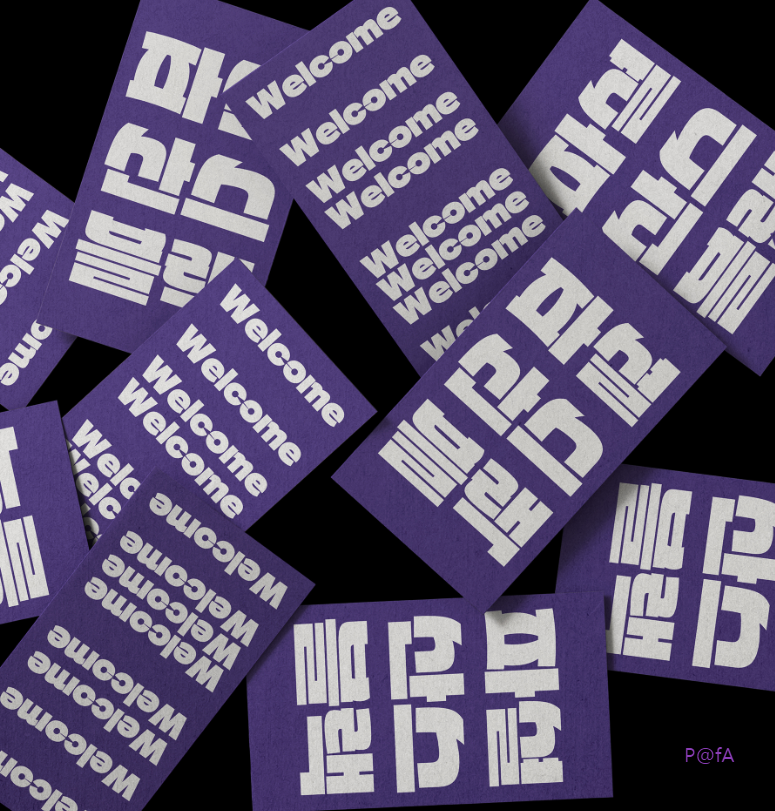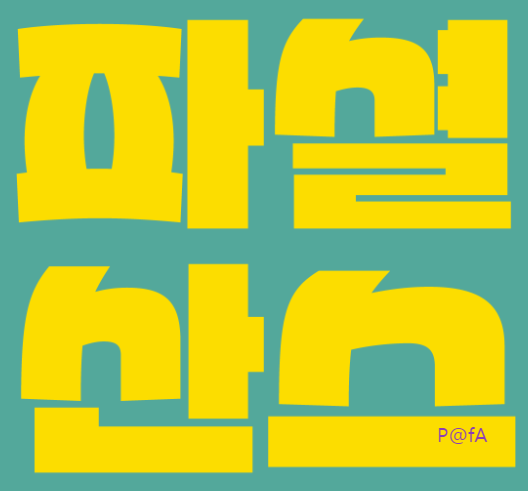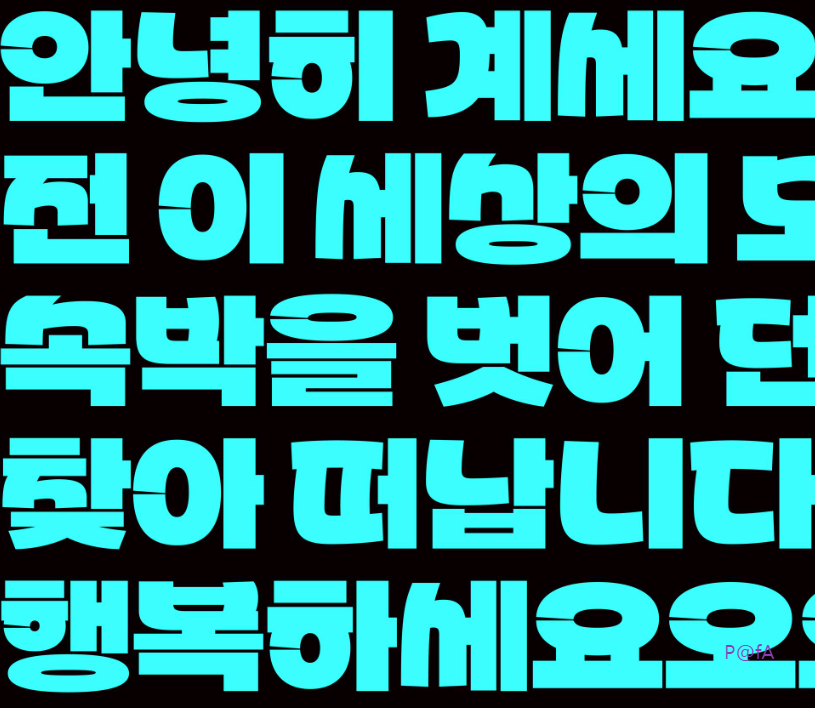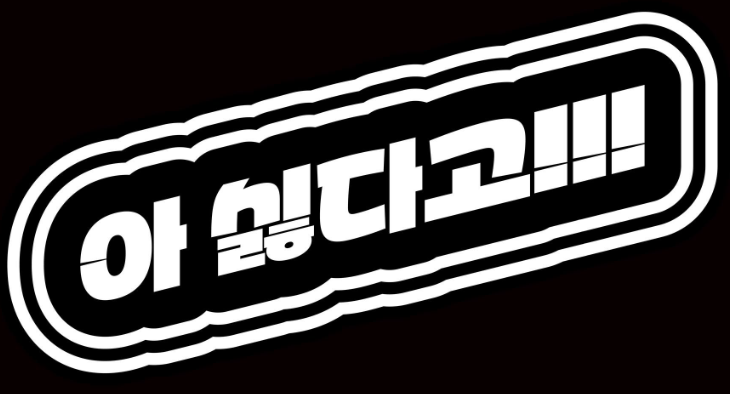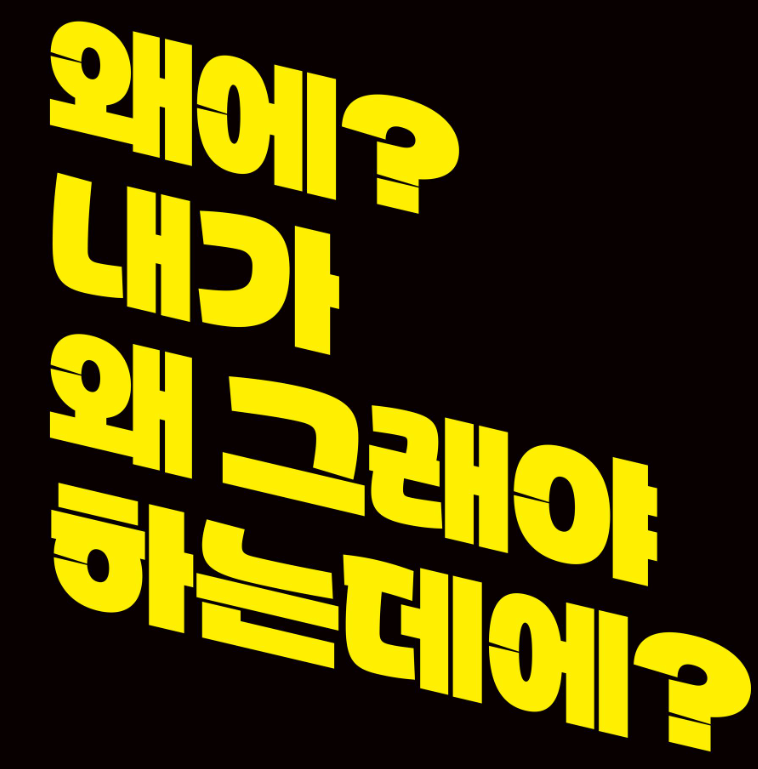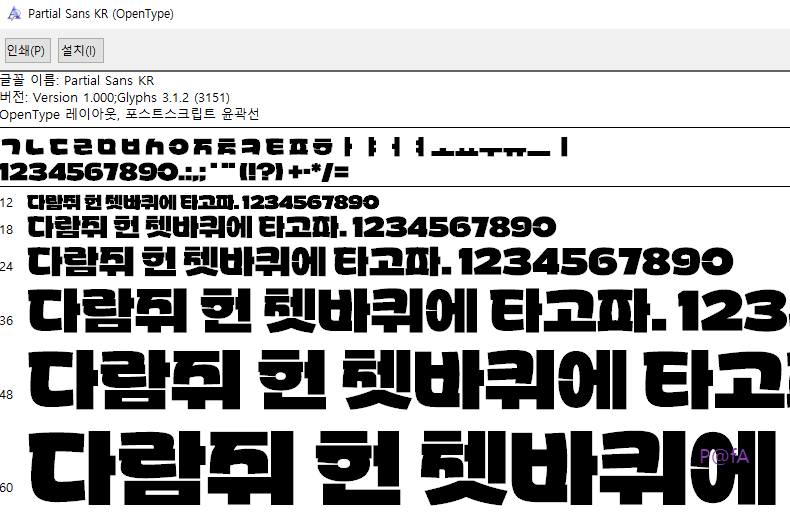
개인 제작자인 박준영 그래픽 디자이너가 제작해서 무료 폰트로 제공하는 파셜산스를 무료로 다운로드하는 방법을 살펴본다. 더불어 누구나 무료로 사용이 가능한 파셜산스를 컴퓨터에 설치하는 방법과 코딩 시에 사용하는 방법도 살펴본다.
그래픽 전용 장식체 파셜산스
파셜산스는 전체적으로 장식체로 시선을 주목하게 하는 도드라진 글꼴 형태로, 일반적인 문서 작업보다는 디자인이 필요한 그래픽 작업에 제격인 폰트이다.
위의 이미지에서 보듯이 ㅇ과 ㅎ에서 좌측 중간이 끊긴 모양이 대표적인 특징인데, 이외에도 전체적으로 두꺼운 획과 동그란 형태를 보이면서 각각의 불균형한 자소로 안정적인 글꼴 형태를 완성한 어울림이 인상적인 폰트이다.
이렇듯 파셜산스는 자소의 불균형 매치로 호불호가 갈릴 수밖에 없는 폰트로, ㅇ의 단절된 형태와 대다수 자소에 과한 곡선 처리로 짧은 문장에서는 가독성을 잃지 않으면서 강렬한 인상으로 주목도가 높아서 타이틀 또는 홍보용 서체로 어울리는 전형적인 장식체이다. 즉, 장식체이기에 사용할 수 있는 범위가 한정되어 있을 수밖에 없는데, 특히 레포트 등 문서 작업에서 사용은 가급적 삼가야 하는 폰트의 특징을 지니고 있다.
더불어 해당 폴더 보기 옵션을 아주 큰 아이콘으로 변경하면 해당 파셜산스 글꼴 파일을 미리 볼 수 있어 유용하다. 위에서 보듯이 ㅎ에서 좌측 중간이 단절된 형태와 ㄱ이 도톰하면서도 곡선 형태임을 명확히 확인할 수 있다.